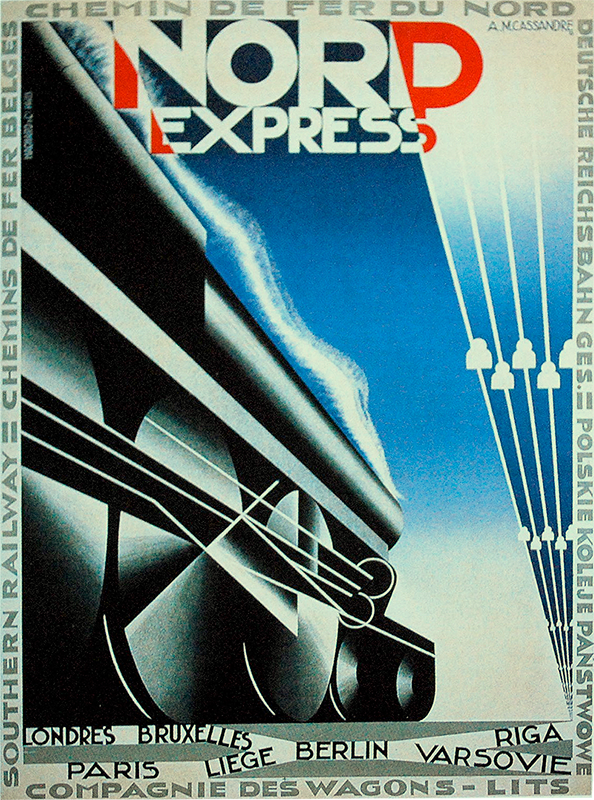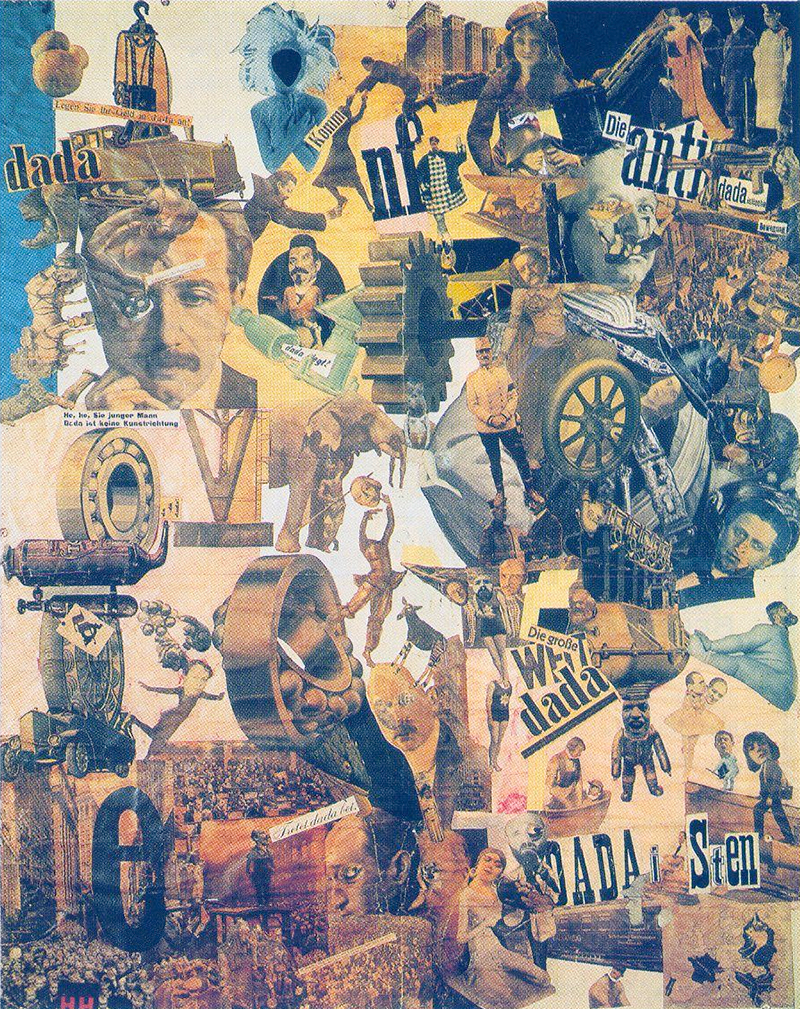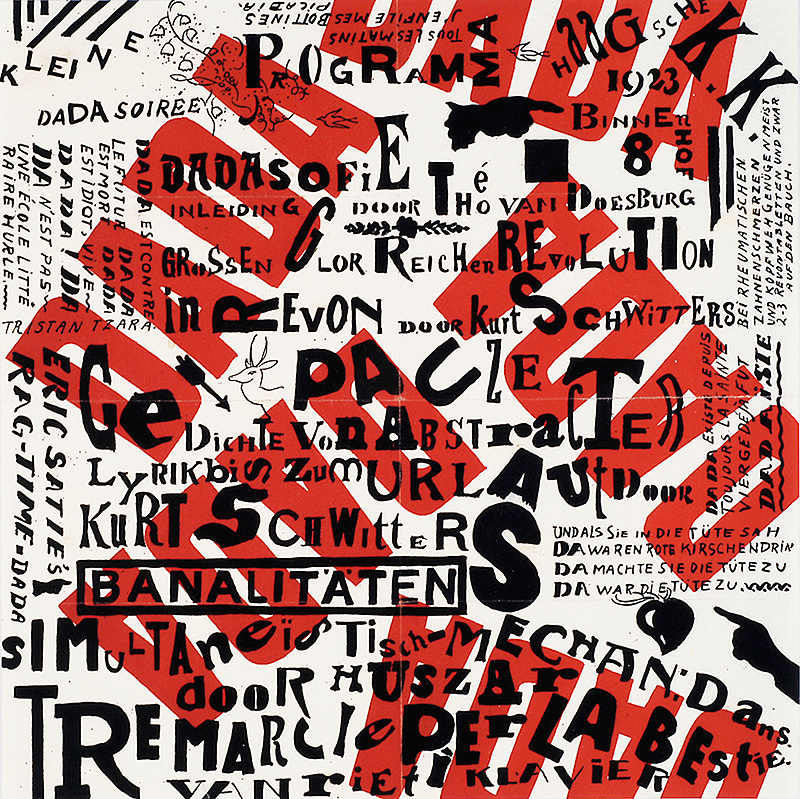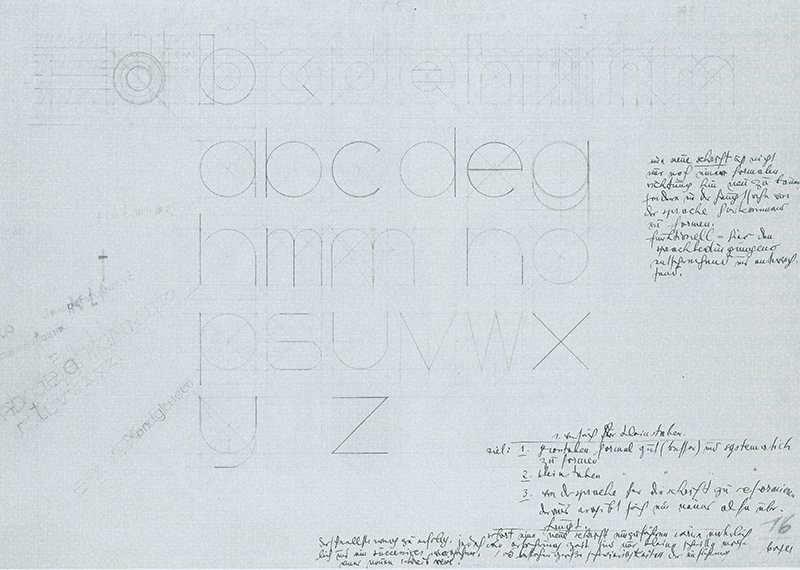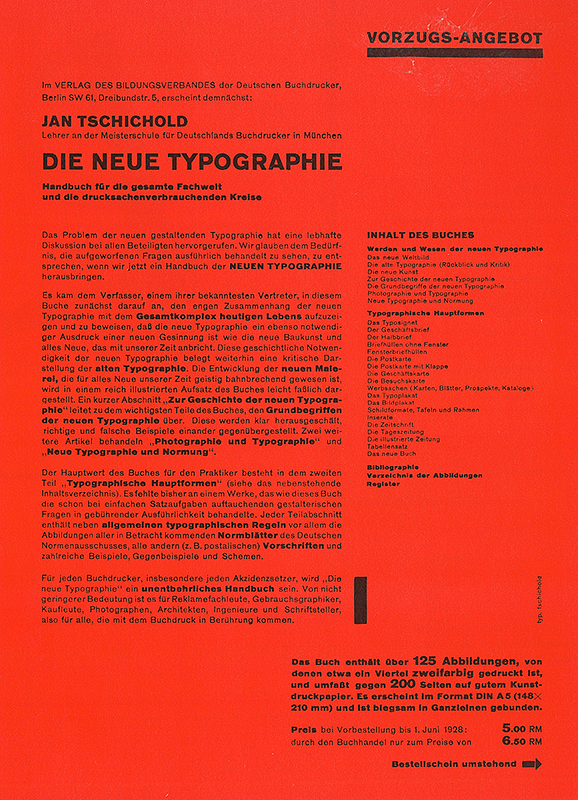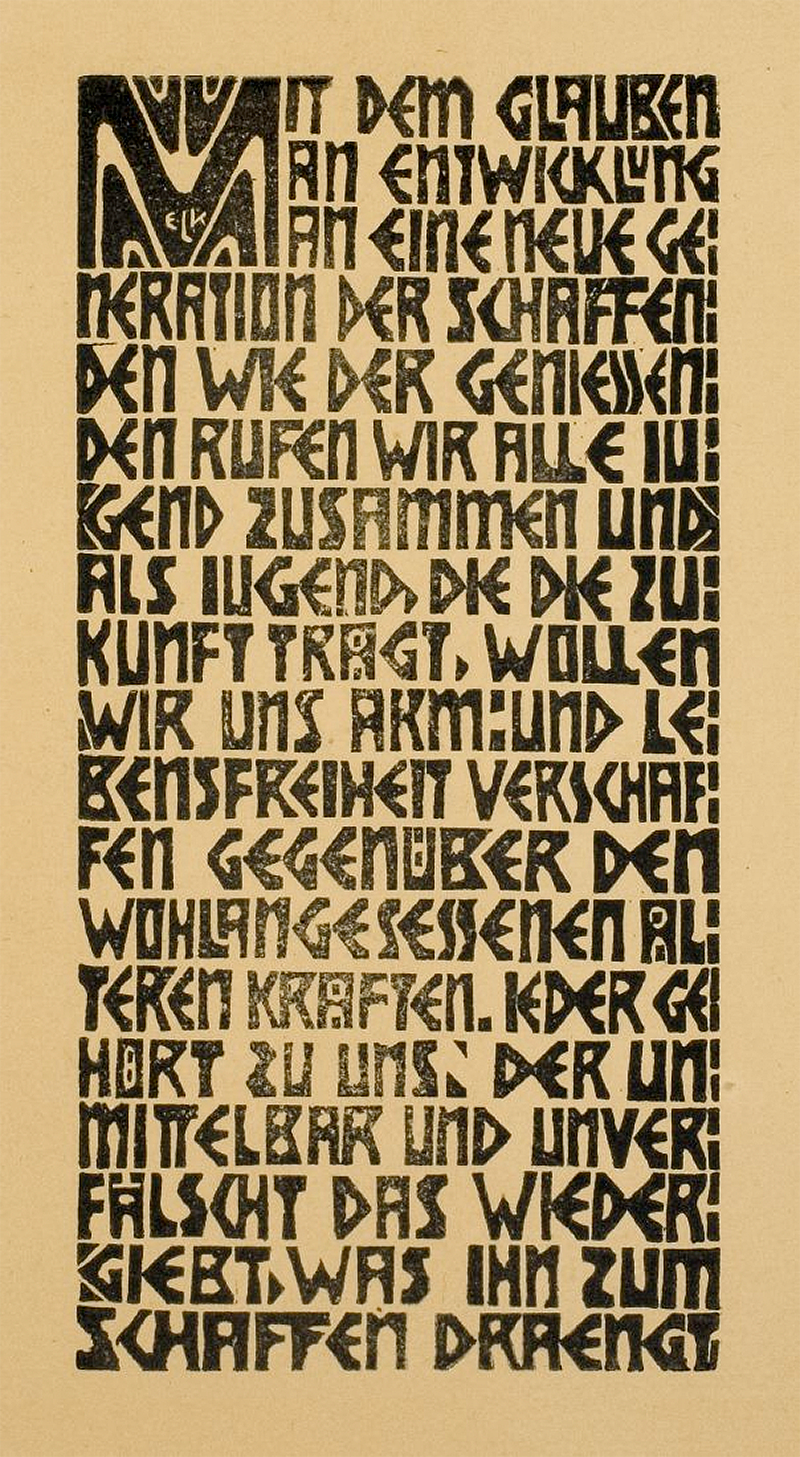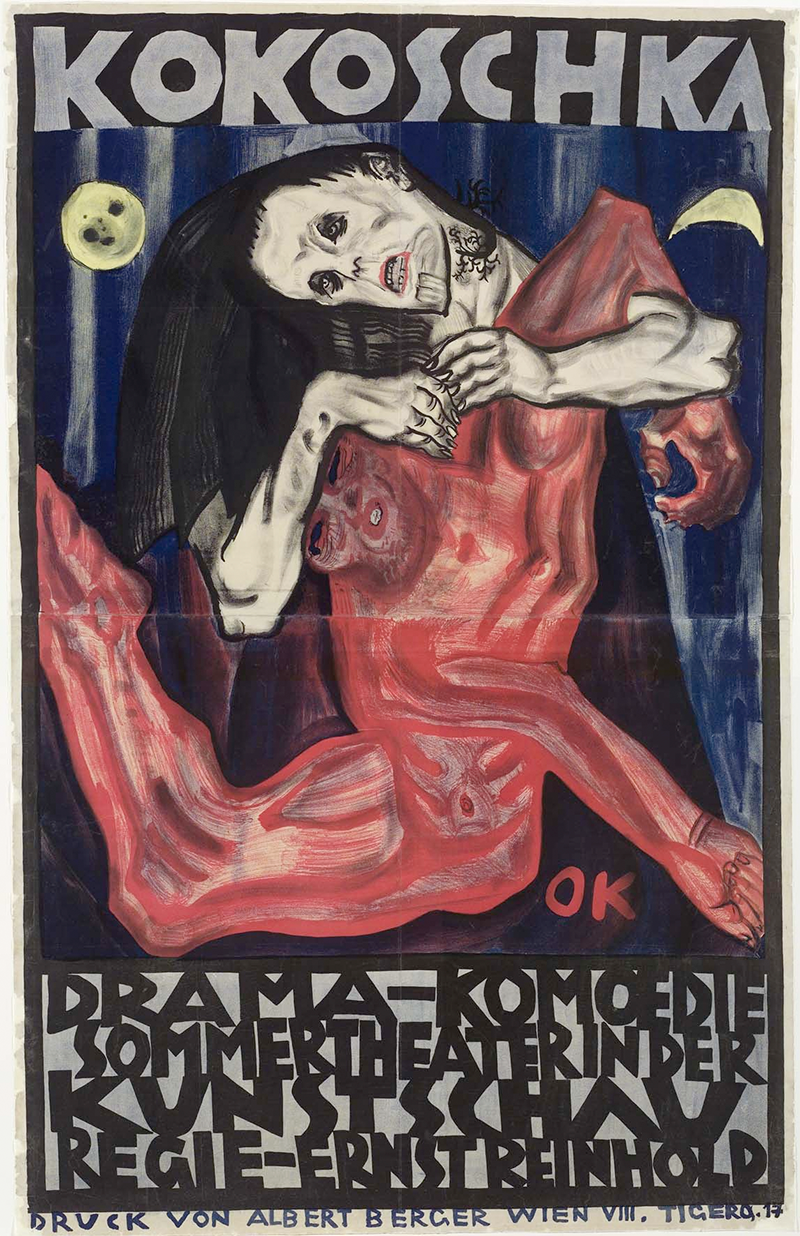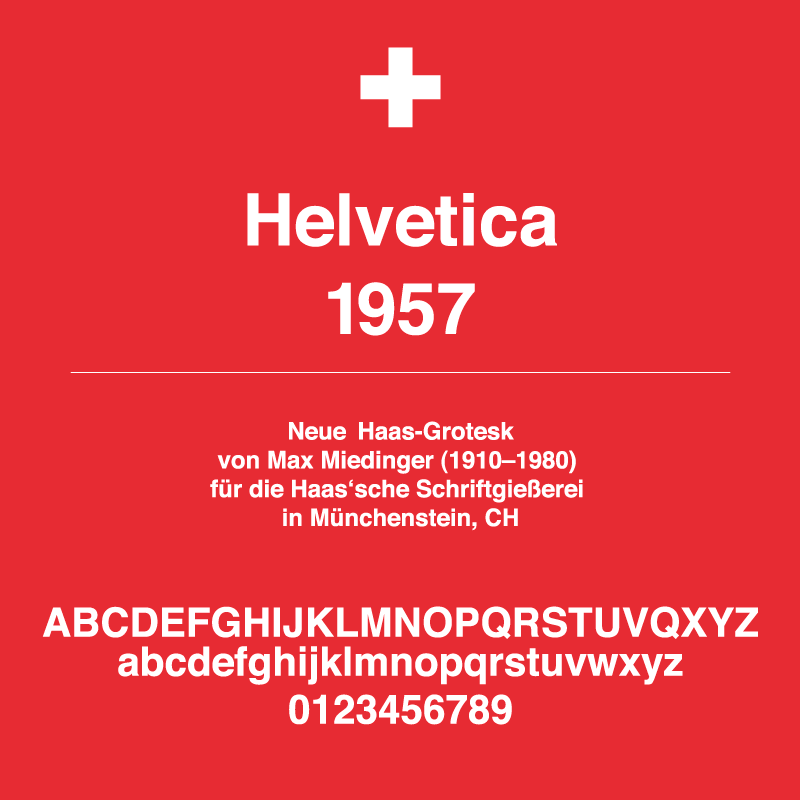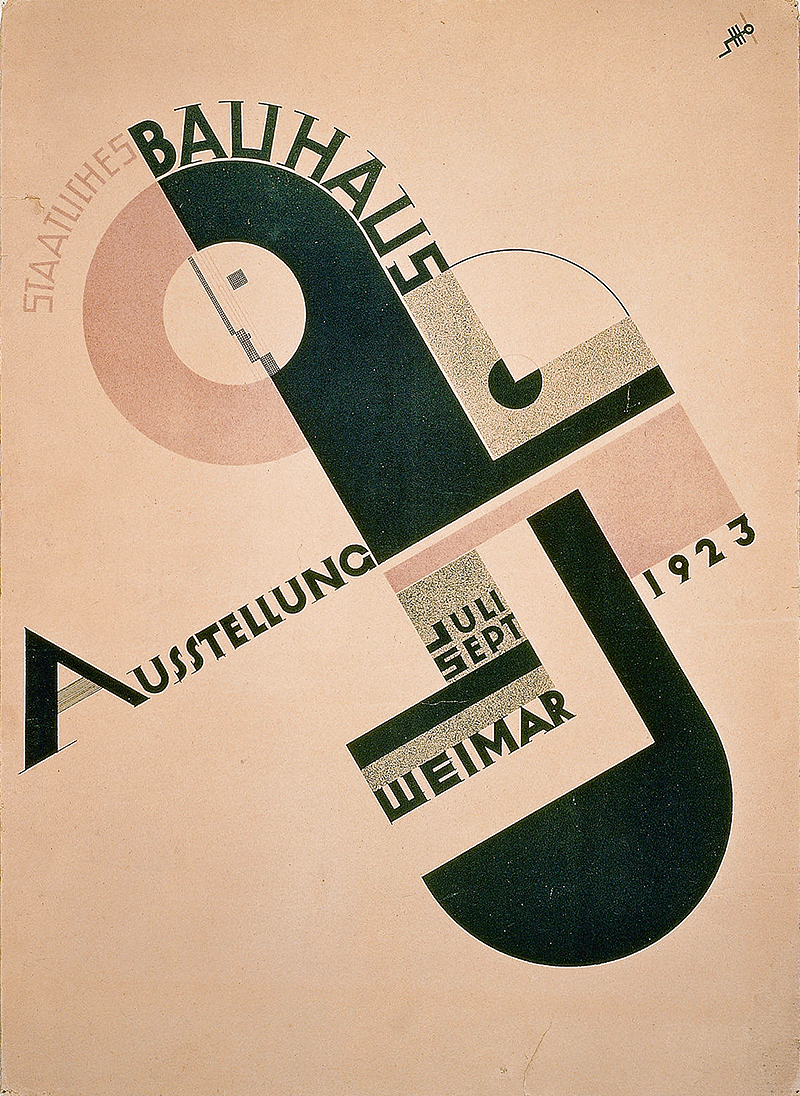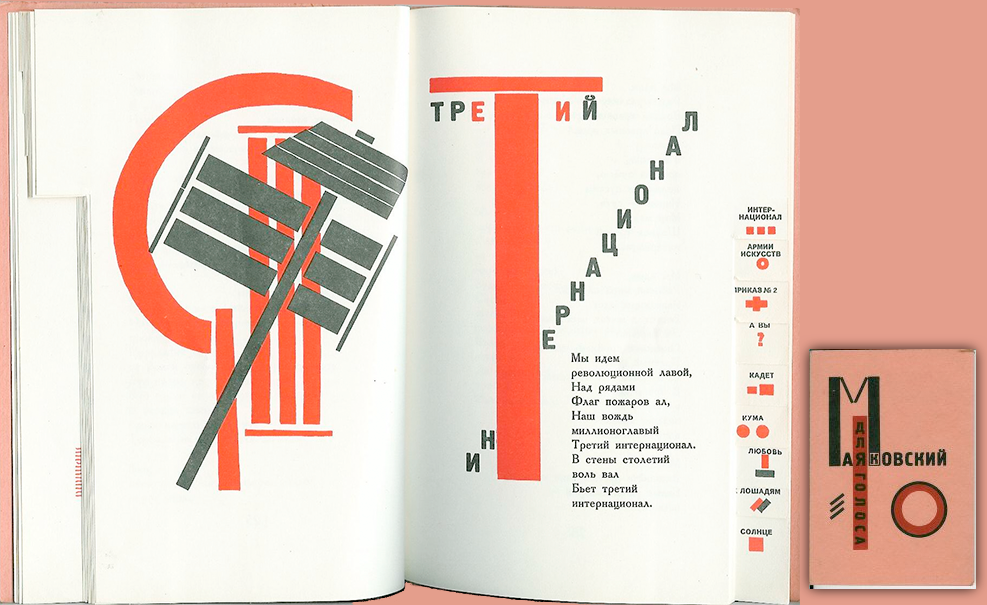
Über eine Entwicklung der Schrift im herkömmlichen Sinn kann man im XX. Jahrhundert nicht mehr sprechen. Die Antiqua und die Fraktur wurden in den vergangenen fünf Jahrhunderten perfektioniert. Die Groteskschriften, die zunächst für Akzidenzen entstanden sind, werden diesem Prozess erst unterzogen. Das XX. Jahrhundert nimmt zunächst den industriellen Aufschwung der „Arts & Crafts“ Epoche sowie die dekorative Ornamentik des Jugendstils auf. Die Schrift selber wird einem Mode-Wandel unterzogen und an die jeweiligen Strömungen angepasst (manchmal sogar missbraucht): sei es an die informative Sachlichkeit der Industrie, an die „-Ismen“ (Futurismus, Dadaismus, Konstruktivismus, Expressionismus), Art Deco oder die Elementare Typografie des Bauhauses usw. |
Futurismus: die Befreiung des Wortes |
Diese in Italien um 1909 entstandene Bewegung ist die erste avantgardistische Strömung des Jahrhunderts. Programmatisch nimmt sie das Wort „futuro“ (it. Zukunft) in ihr Manifest auf, verwirft alles langsame, konservative, unmoderne, traditionsbehaftete (= passatistische) und schreibt „Freiheit“ auf ihre Fahnen. Futurismus – verglichen mit anderen Bewegungen des beginnenden Jahrhunderts – bedient sich am häufigsten der Typografie (Lettrismus). Interessant sind für die Futuristen vor allem die Wörter, während die Buchstaben selbst nur für gestalterische und optofonetische Zwecke gebraucht werden. 38 Der literarische Inhalt bleibt meist unangetastet, doch der Akt der „gestalterischen Befreiung“ reizt die Futuristen.
Die Glyphen selbst werden in verschieden Größen und Farben, in verschiedenen Stilen und Familien nebeneinander gesetzt; die mathematischen Zeichen ‚+‘ und ‚=‘ werden gebraucht, „um gewisse Bewegungen hervorzuheben und ihre Richtung anzugeben“. 39 Ein Aspekt sorgt bei den italienischen Futuristen für Kontroverse: die Kriegsbegeisterung. Dabei sollte berücksichtigt werden, dass die futuristischen Manifeste vor den Weltkriegen entstanden, dass die Futuristen den globalen, sinnlos vernichtenden, kampfstoffeinsetzenden Krieg noch nicht erlebt haben und diese radikalisierende Äußerung den Blick auf die gesamte Bewegung – pauschal genommen – schlicht und einfach verfälscht: „Wir wollen den Krieg verherrlichen – diese einzige Hygiene der Welt –, den Militarismus, den Patriotismus, die Vernichtungstat der Anarchisten, die schönen Ideen, für die man stirbt, und die Verachtung des Weibes.“ (Filippo Tommaso Marinetti, Futuristisches Manifest, 1909). Marinetti wollte radikale Veränderung der Welt und der Kunstszene – doch nicht um den Preis von Menschenleben! Zu den führenden Futuristen aus typografischer Sicht zählen in Italien: Filippo Tommaso Marinetti (1876–1944), Emma Marpillero (1896–1985) und Carlo Dalmazzo Carrà (1881–1966), in Russland sind es die Mitglieder der Hyläa-Gruppe: Welimir Chlebnikow (1885–1922), Alexei Krutschonych (1886–1968) und Wladimir Majakowski (1893–1930). |
Dadaismus: Anarchie und Ablehnung um jeden Preis |
Das Versagen der abendländischen Kultur und ihrer gesellschaftlichen Strukturen, das sich im Ausbruch des Weltkriegs manifestiert hat, führte zur Entstehung einer Protestbewegung, die grundsätzlich gegen Alles gerichtet war. Der aus der ablehnenden Haltung heraus entstandene Dadaismus definiert sich dadurch, dass er nicht definierbar sei.
Ab Februar 1916 treffen sich die Gründer im „Cabaret Voltaire“ in Zürich, um die s. g. „Dada-Soiréen“ zu veranstalten. Hier bringen sie ihre ablehnende Haltung gegenüber der Verlogenheit der bürgerlichen Gesellschaft zum Ausdruck. Anarchie und Provokation, Individualismus und Nihilismus, Sarkasmus und Spott sind Mittel, die die Gesellschaft verunsichern, verwirren und zum Nachdenken zwingen sollen. Die herrschenden Auffassungen und Wertvorstellungen sind Illusion – der fortgeschrittene Bürger befreit sich davon und nimmt an der Erschaffung einer ehrlichen Welt teil. Die Bewegung erreicht mit ihrer revolutionären Haltung bald New York, Paris und Berlin. Die Dadaisten laden die Künstler zum Umdenken ein – so eröffneten sie den Zugang zu neuen Sicht- und Denkweisen. Antikunst lautet die Devise. Zufall ersetzt die Planung. Die Stile werden untereinander gemischt: Literatur, Bild, Typografie, Ton und Theater werden in bruitistischen Spektakeln zusammengeführt. „Selten in der Geschichte waren der inhaltliche Anspruch und die umgesetzte Form so eng zusammen und bedingten sich geradezu wie bei den Lautgedichten und akustischen Collagen, die eine neue Poesie hervorbrachten.“ 40 Typografisch bietet Dadaismus eine gewisse Ästhetik und Originalität. Durch den Bruch mit den Konventionen wirkt er erfrischend und herausfordernd: „Die Dada-Typografie war für die Werbegestaltung oder Informationstypografie völlig ungeeignet. Auf individuelle,gestalterische Versuche wirkte diese befreite und befreiende Gestaltung seit damals immer wieder sehr anregend und erneuernd. Handwerkliche Setzerregeln wurden völlig missachtet. Es wurden unfachliche Schriftmischungen in Schräg- und Rundsatz collagiert, die Buchstaben und Wörter tanzten wie in freiheitlicher Entrückung über die Formate. So wurden Einzelbuchstaben zu Bildelementen in einer Gesamtkomposition. Gewohnte Textabläufe wurden zugunsten optischer Bildüberlegungen zerteilt.“ 41 Berühmteste Vertreter des Dadaismus: Marcel Duchamp (1887–1968), Francis Picabia (1879–1953), Man Ray (Emmanuel Radnitzky) (1890–1976), Raoul Hausmann (1886–1971), John Heartfield (H. Franz Josef Herzfeld) (1891–1968), Hannah Höch (1889–1978), George Grosz (1893–1959), Hans Richter (1888–1976), Viking Eggeling (Hellmuth Viking Fredrik) (1880–1925), Kurt Schwitters (1887–1948), Max Ernst (1891–1976), Hans (Jean) Arp (1886–1966) |
Konstruktivismus: gegenstandslose Komposition der Geometrieformen |
Der Sieg der Revolution in Russland bedeutet vorerst das Ende der traditionellen Kunst. Neue, dem herrschenden Volk angepassten Darstellungsformen, die das Kollektiv objektiv repräsentieren, werden gefragt. Nicht Individualisten, sondern Kunst-Ingenieure sollen neue Form- und Ausdruckssprache für die Kommunisten finden. Revolutionärer als bei Kasimir Malewitschs Bildern „Schwarzes Quadrat auf weißem Grund“ oder „0,10“ (1913–1915) geht es nicht mehr. Gerade dieser Bruch mit der Tradition, die Radikalität und Einfachheit ermöglichen es den Nachfolgern, mit dem Vokabular der geometrischen Formen zu experimentieren. Es entstehen Bücher, Plakate, Collagen und Illustrationen, die lediglich mit den Mitteln der konstruierenden Montage arbeiten. Spartanisch, dynamisch, manchmal gelungen und schön.
Wie jede avantgardistische Mode des XX. Jahrhunderts verbreitet sich der Konstruktivismus in Europa. El Lissitzky verbringt vier Jahre in Deutschland, wo er auch am Bauhaus tätig ist. Die konstruktivistischen Bauhaus-Tendenzen stammen direkt aus dem Sowjet. Die Idee erreicht bald Niederlande (Mondrian und „De Stijl“), Polen, Jugoslawien und Tschechoslowakei. Für die Konstrukte wird auch die Typografie verwendet: einzelne Buchstaben übernehmen häufig gestalterische Aufgaben und werden zu Sinnbildern der Botschaft. Die Antiqua- und Frakturschriften sind für die Kinder der Revolution zu rückständig. Die modernen Alphabete bestehen meist nur aus Versalien, übermitteln Kurzbotschaften in Stichworten und sind keinesfalls mengentexttauglich. Durch die Konstruktivisten ist der Weg für die geometrische Konstruktion der Groteskschrift geebnet. Russland selbst ist nach wenigen Jahren der Begeisterung für den Konstruktivismus mit den reduzierten, abstrakten Aussagemitteln nicht zufrieden. Totalitäre Systeme bevorzugen Nationalrealismus mit Bildern von zufriedenen und starken Menschen. Konstruktivismus wird diffamiert und später sogar verboten. Ähnliches Schicksal erwartet wenige Jahre später die Avantgardisten im Deutschland. Bedeutende Konstruktivisten: Kasimir Malewitsch (1879–1935), Piet Mondrian (1872–1944), Willi Baumeister (1889-1955), El Lissitzky (1890–1941), László Moholy-Nagy (1895–1946), Thilo Maatsch (1900-1983). |
Expressionismus: Ausdruck des verletzten Individualismus |
Basierend auf den ausdrucksintensiven Bildern Vincent van Goghs (1853–1890) und Edvard Munchs (1863–1944) spiegelt der um 1910 entstehende Expressionismus das Lebensgefühl einer jungen Generation, die einerseits aus den starren Rahmen der gleichgültigen und verlogenen Gesellschaft auszubrechen versucht, andererseits die durch die Industrialisierung und Politik verletzte individuelle Seele zum Ausdruck bringen möchte.
Das Ur-Menschliche des Afrikanischen und Ozeanischen, das die Völkerkunde-Museen zu Beginn des Jahrhunderts füllt, wird neu entdeckt und erforscht. Die junge Psychoanalyse Freuds bringt weitere Impulse für die Suche nach dem eigenen „Ego“. Nietzsche wird zum Ziehvater des Expressionismus erklärt: alles wird in Frage gestellt. Spontaneität und „das individuelle Erleben“ des Motivs sollen im (bildlichen) Ausdruck spürbar und nachvollziehbar sein. Eines der bevorzugten Mittel des künstlerischen Ausdrucks der Expressionisten ist der Holzschnitt. Das Grobe an Materialien und Werkzeugen erlaubt zügiges und spontanes, ja expressives Arbeiten. Die Typografie des Expressionismus ist ausdrucksstark und innovativ, überzeugend und individualistisch; sie ist somit für Plakate, Buchumschläge oder Akzidenzen gut zu gebrauchen – für den Satz längerer Texte jedoch völlig ungeeignet. Sie bedient sich häufig der Steinlithografie, des Linol- und des Holzschnitts. Bedeutende Expressionisten: Ernst Ludwig Kirchner (1880–1938), Erich Heckel (1883–1970), Max Pechstein (1881–1955) Wassily Kandinsky (1866–1944), Alexej Jawlensky (1865–1941), Franz Marc (1880–1916), Oskar Kokoschka (1886–1980) Gabriele Münter (1877–1962), Marianna Werjowkina (1860–1938). |
Art Deco: Eleganz des Ausdrucks |
Die Grundsätze der Wiener Werkstatt, die die gewerbliche und industrielle Seite des Jugendstils um die Jahrhundertwende repräsentiert, gelten auch für die Gründer der Art Deco Bewegung: sie wollen die Welt schöner machen. Der Konsument wird mit der Eleganz der Form und Kostbarkeit der verwendeten Materialien angelockt.
Die Gesellschaft hat Gründe zu feiern: der Weltkrieg ist zu Ende, die Welt ist elektrifiziert, sie swingt, jazzt und feiert aus allen Röhren. „…(der) typografische Stil ging (…) von einer Anreicherung der elementaren Formen mit Ornamenten und mit vielfältigem Dekor. Neben dem geometrischen Ansatz gehören florale und figurative Motive, die in kubischen Abstraktionen verwandt wurden, zu den Hauptmotiven des Art Deco. Es entstanden modisch-zeitgeistige Chiffren, die in den Niederlanden, Frankreich, England, in der Schweiz, in den osteuropäischen Ländern und den USA zu großer Blüte und Verbreitung kamen.“ 42 Die Schriften werden nicht direkt aus den geometrischen Formen konstruiert, sondern entfalten eine Wechselwirkung: von breit zu schmal oder von hell nach dunkel. Häufig wird optische Täuschung in der Verspieltheit der Linien angewandt oder der Versuch unternommen, räumliche Wirkung zu erzielen. Die Lesbarkeit der Texte ist zweitrangig: was zählt ist die Dekoration. Einige Art Deco-Vertreter: K. Hlavaček (1874–1898), A. M. Cassandre (1901–1968), E. McKnight-Kauffer (1891–1954), J. Carlu (1900–1997), A. Brodovitch (1898–1971). |